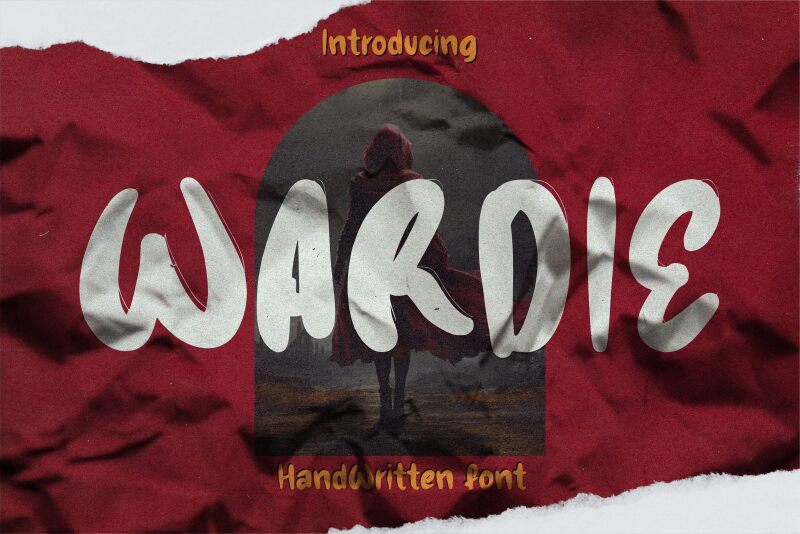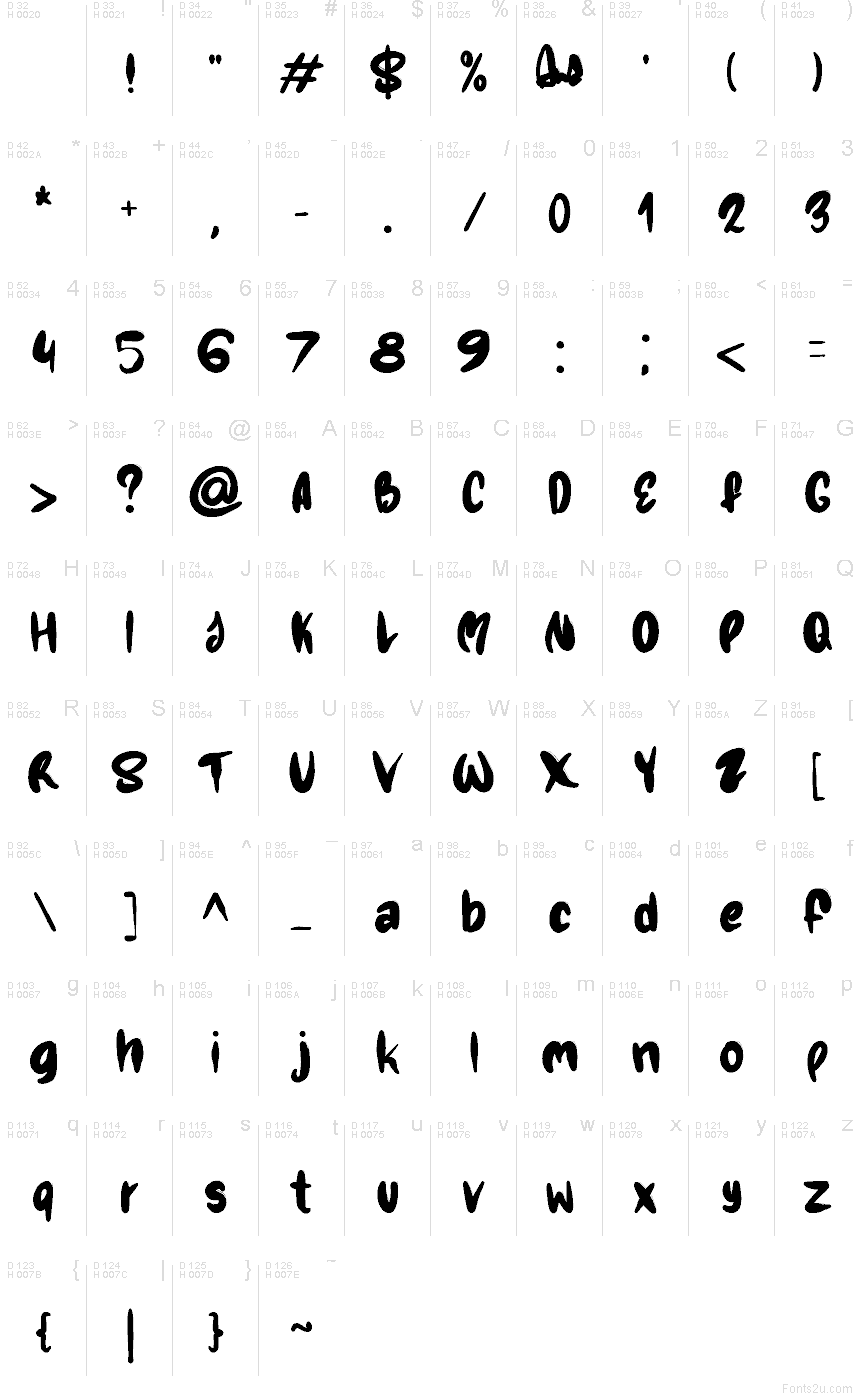
Náhled písma WARDIE
WARDIE je bezplatné písmo s efektem mokrého štětce, jehož sytá silueta působí, jako by byla každá litera na papír spíše vylita než pečlivě kreslena. Široké, zaoblené tahy a lehce nepravidelný rytmus dodávají písmu ležérní nádech ručního nápisu, zatímco měkké zúžení v obloucích zabraňuje dojmu strnulosti.
Tato textura dodává krátkým titulkům na obalech, v kavárenských menu, na letácích, plakátech i grafikách pro sociální sítě silný vizuální charakter. WARDIE se skvěle hodí také pro nálepky a návrhy log, kde mají baculaté tvary štětce působit řemeslně, přátelsky a spontánně, místo aby vypadaly příliš vyhlazeně či strojeně.